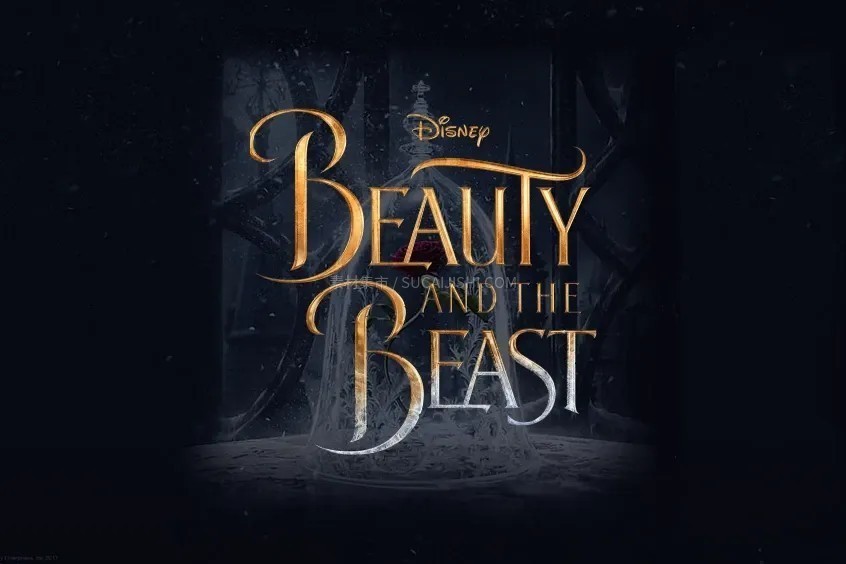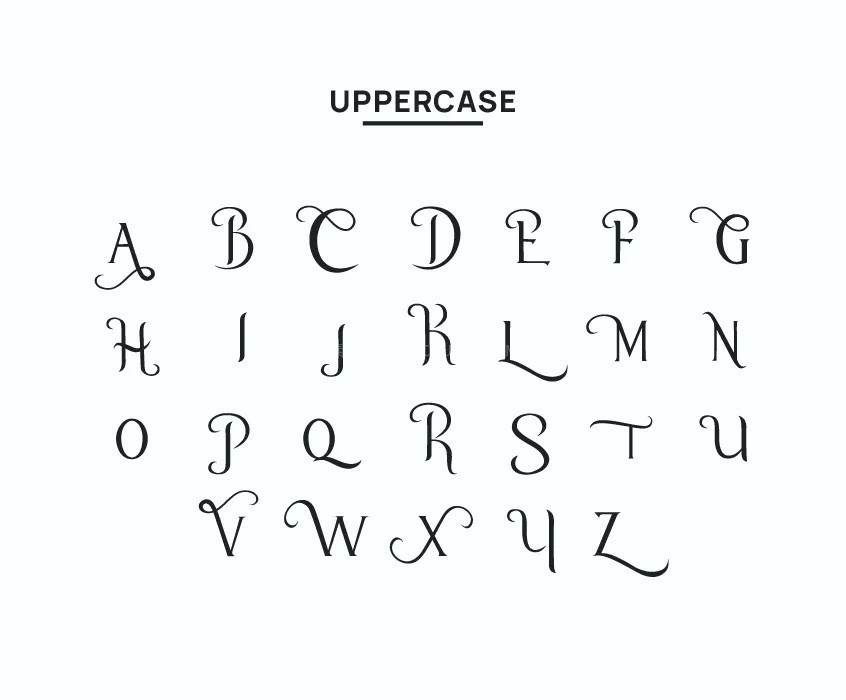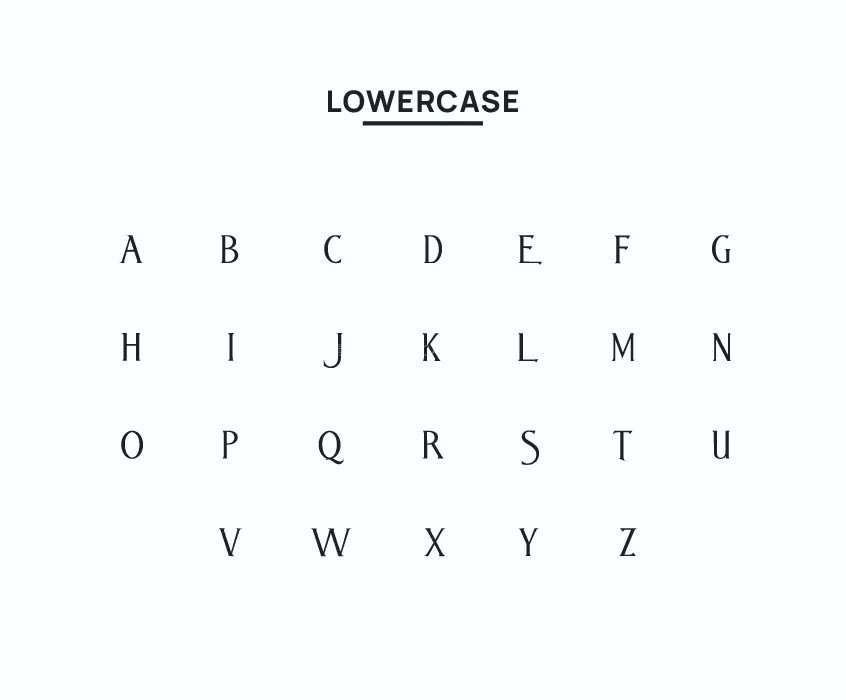
《美女与野兽》同款奇幻英文字体
这是设计师 JoannaVu 在 2018 年致敬《美女与野兽》经典电影海报精心重设的字体。它是一款自带高级感的复古衬线体,特别是在字母“B”和“T”等细节上加入了超绝的华丽装饰笔画,奇幻迷人的童话氛围瞬间拉满!字体目前包含 53 个字形和 54 个字符(仅支持拉丁字母)。最棒的是,这款字体开放了免费的非商业用途授权,大家可以毫无负担地存起来,用在自己的个人小项目里哦!